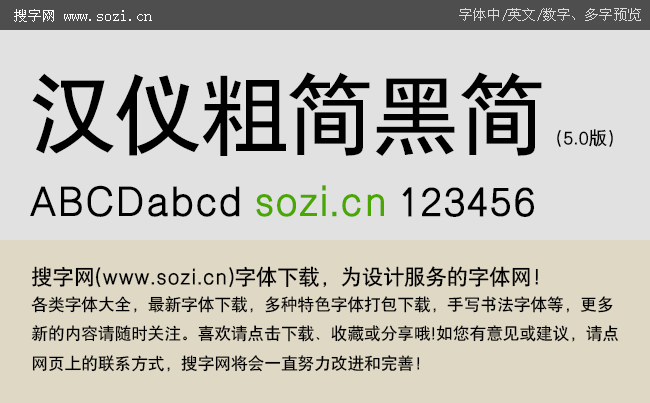
漢儀粗簡(jiǎn)黑簡(jiǎn)
搜字網(wǎng)提供一款漢儀粗簡(jiǎn)黑簡(jiǎn)中文字體下載,漢儀粗簡(jiǎn)黑保持著黑體字的共有特點(diǎn),筆畫粗壯有力,橫豎筆畫粗細(xì)比較接近,兩端平直,加鋒較小,筆畫簡(jiǎn)潔粗壯,厚實(shí)有力。可用于報(bào)刊雜志排版,也適用于平面廣告,圖書印刷等廣告設(shè)計(jì)場(chǎng)合使用。